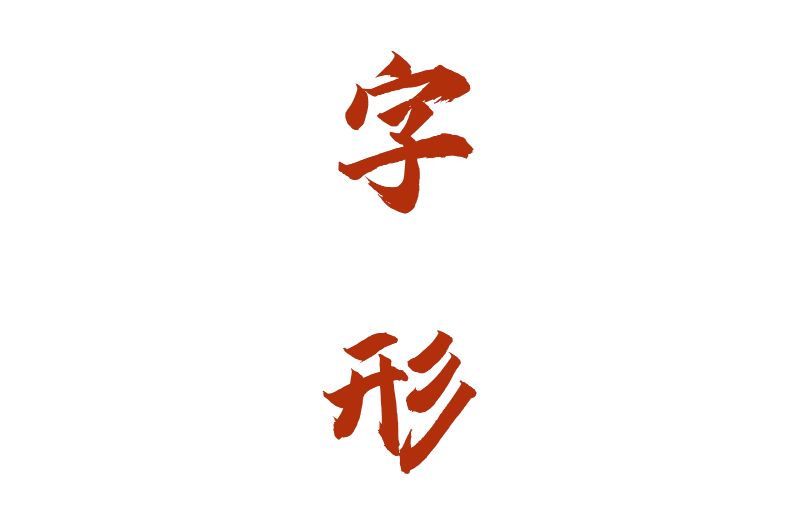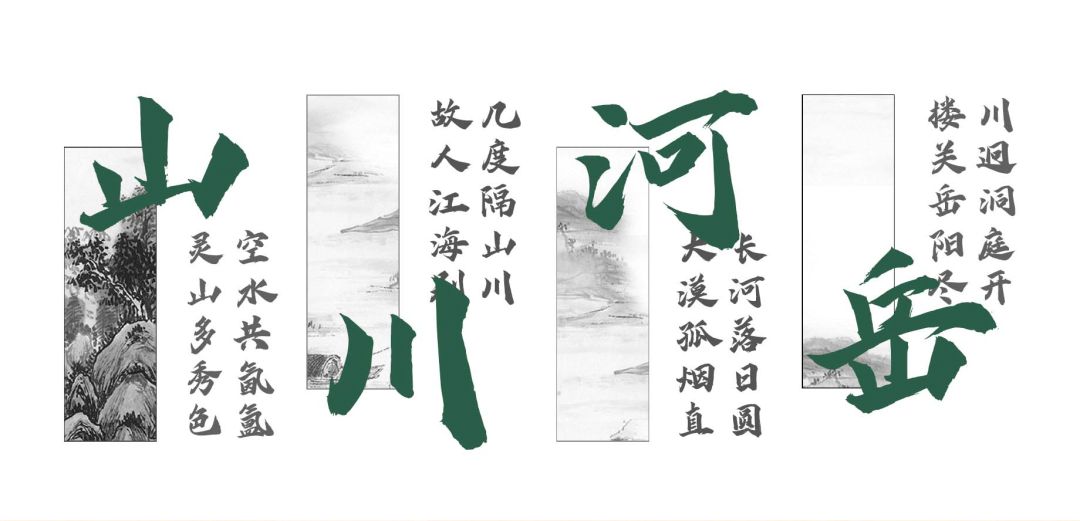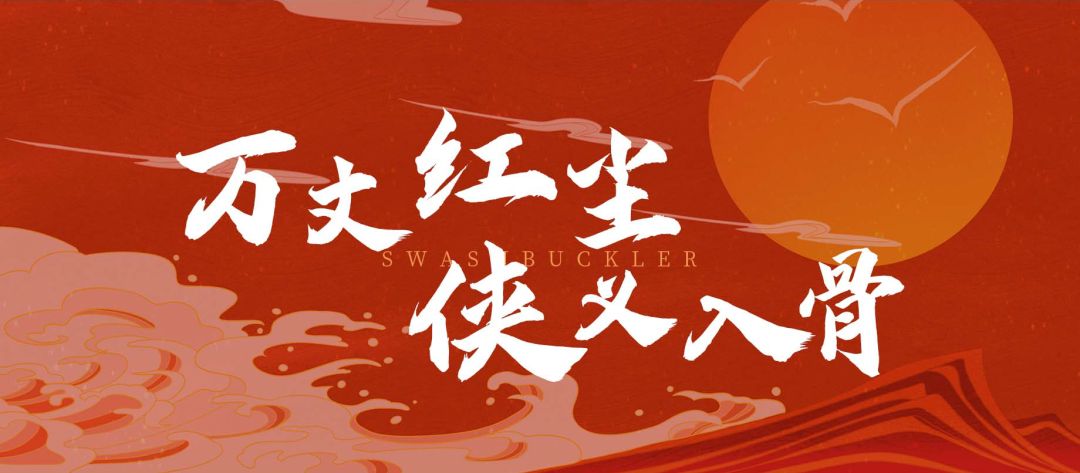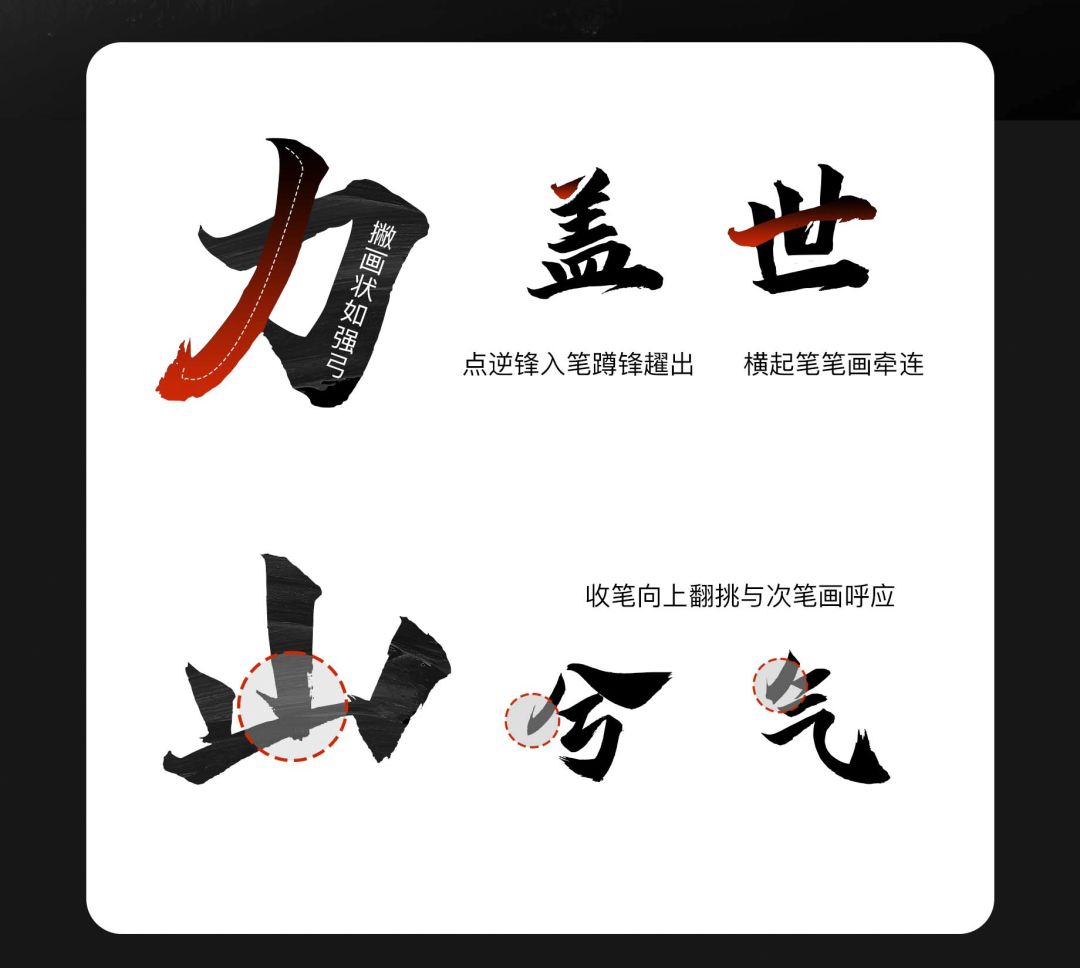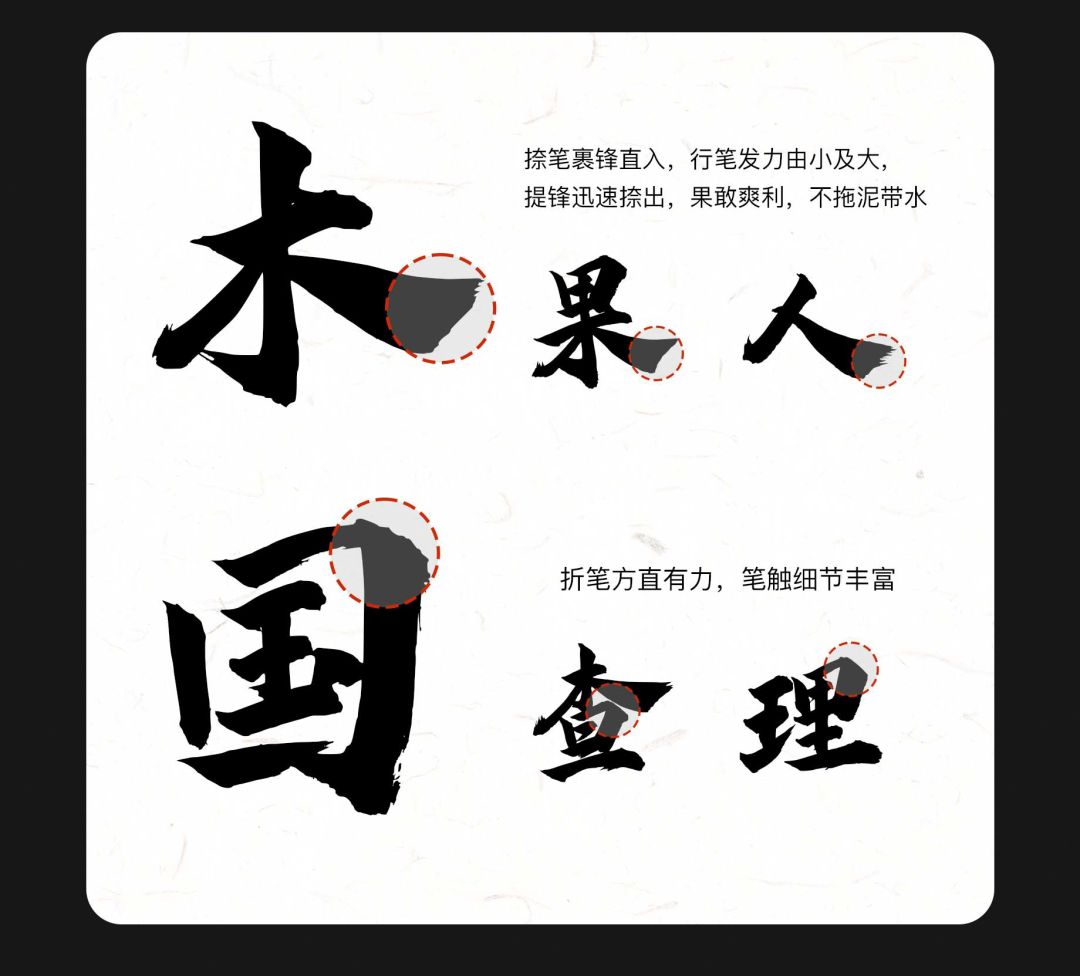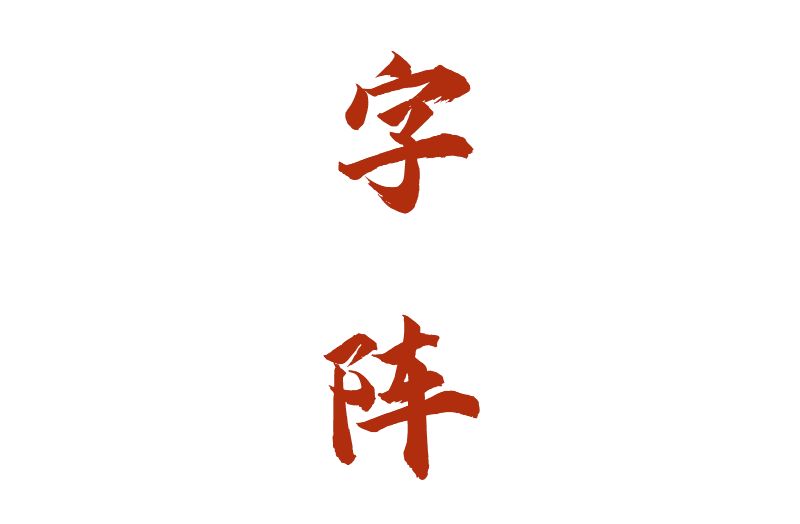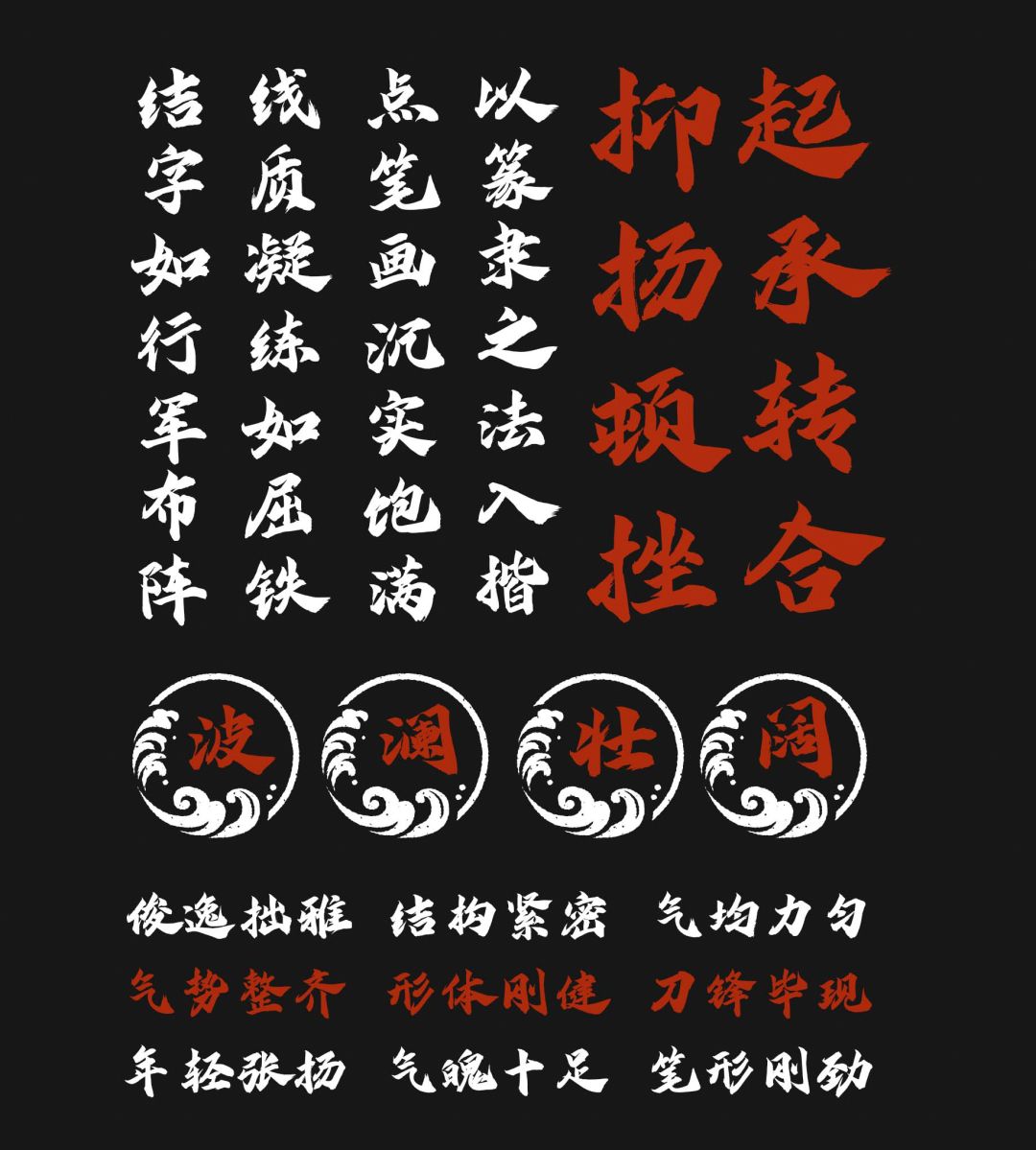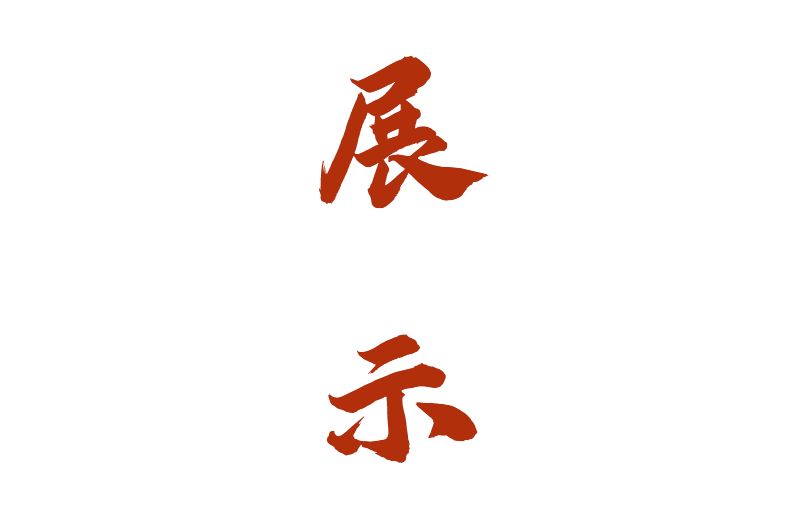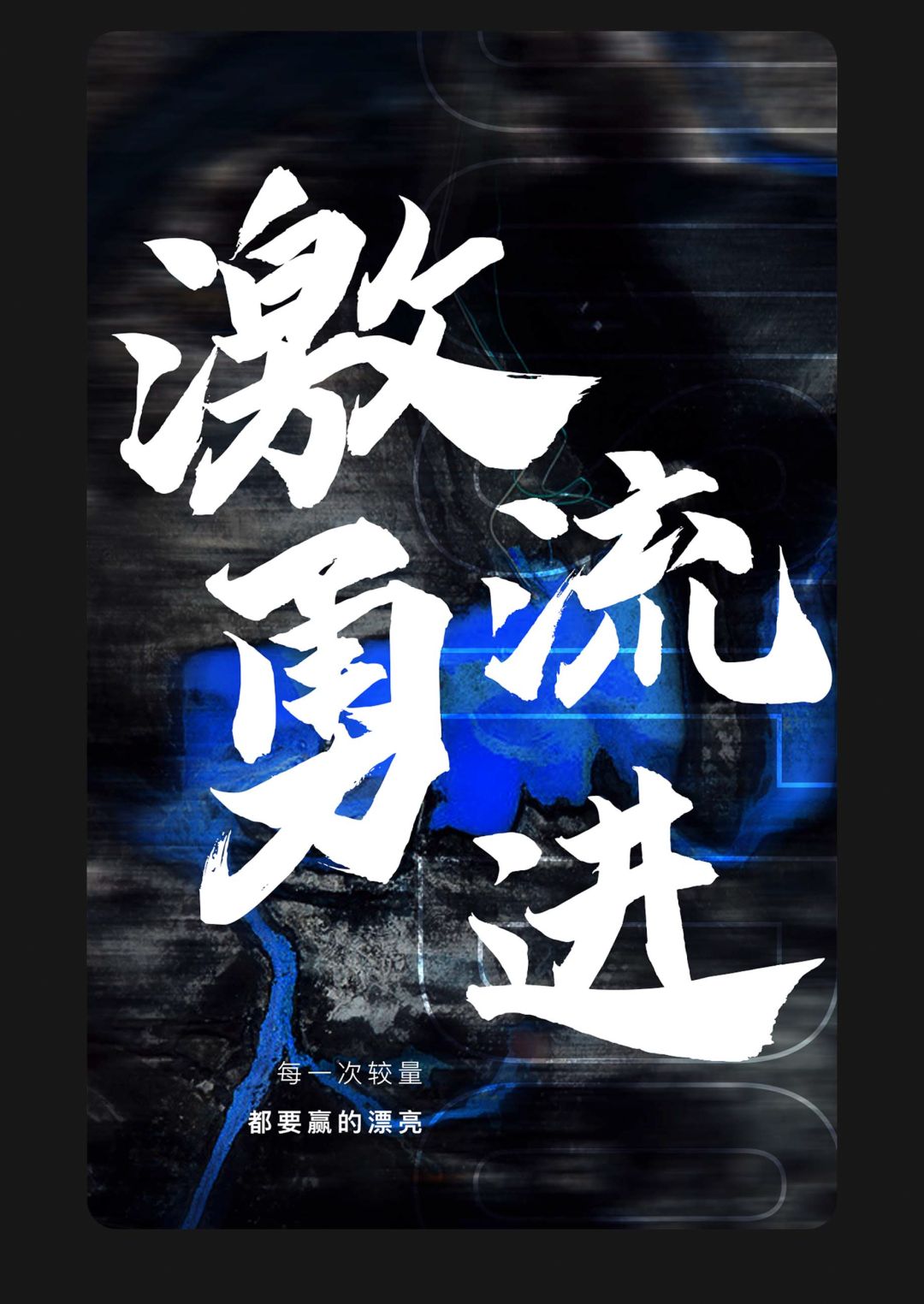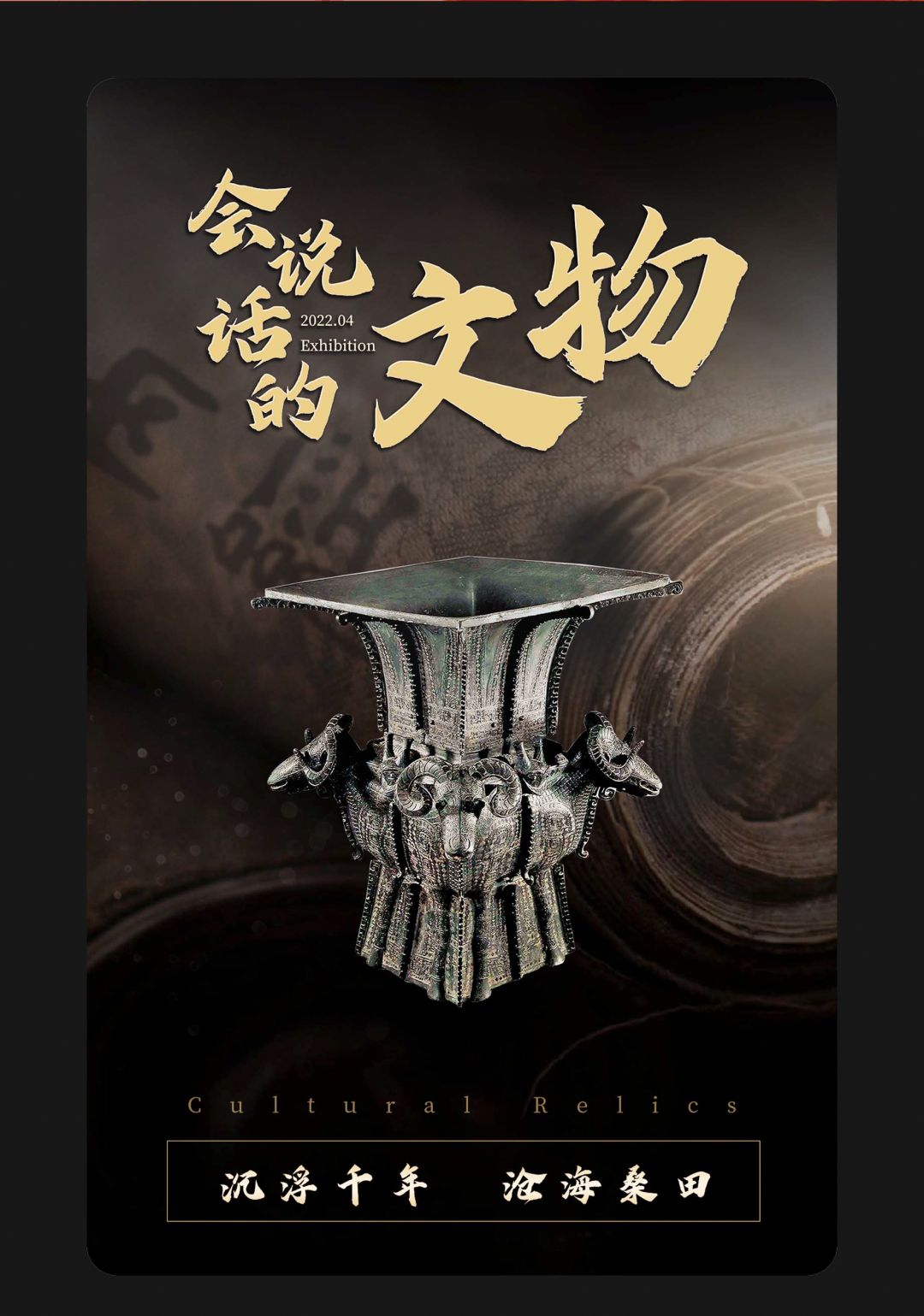
三年前,字魂55号 - 龙吟手书上线
“神龙降世,声闻四野”
字体受到了许多字魂用户们的欢迎
同时几年来也伴随着许许多多
“多出点这类风格的字体”的呼声
在用户们对于经典手书的狂热中
字魂将经典手书字体重塑
龙吟手书兄弟字体:
字魂270号 - 龙门手书
重磅上线!
龙门手书与龙吟手书互为“双璧”,同为将传统笔墨与现代审美结合的字体,在其风格上各有千秋: 龙吟手书蜿蜒华丽,龙门手书则刚劲凝练。 以篆隶之法入楷,线质凝练如屈铁,点画沉实饱满,结字如行军布阵。 字体从传统书法角度出发,体态动势向右上倾斜,与水平形成倾角。 结体上偏左倚斜,跳跃的结构与飘逸但不失严谨的笔画融合在一起,大小变化富有节奏。 用笔以方笔为主,又具圆笔的特征。一方一圆相互穿插、配合。 长撇画状如强弓。 右趯点,逆锋入笔,向左下按继而折笔蹲锋趯出,与下一画成呼应关系。 长横笔画牵连,裹锋逆入,起笔形成纤丝。 收笔向上翻挑与次笔画呼应。 捺起笔裹锋直入,行笔发力由小及大,提锋迅速捺出,果敢爽利,不拖泥带水。 折笔方直有力,笔触细节丰富。 形体刚健,结构紧密,气均力匀,俊逸拙雅,棱角突出,刀锋毕现。 字体气势整齐统一显得年轻张扬,气魄十足,笔形刚劲,起笔锋利,收笔有力。 用笔简洁,用笔画间的呼应关系来表现字体的动势,紧中有放,让单字呈现环环相扣、抑扬顿挫的视觉美感。 龙门手书字体是一款魄力十足,兼具传统与现代美感的字体。 无论是用于现代叙事,还是文艺复古场景,都有不俗的表现力和融合度。 字体具有较强艺术感,适合作为标题进行展示。